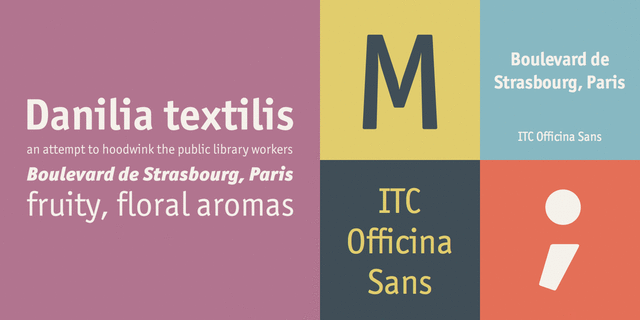
Гарнитура разработана в фирме International Typeface Corporation в 1990 году (дизайнер Эрик Шпикерман). Гротесковая версия шрифта ITC Officina Serif. Основанный на близких пропорциях, насыщенности и форме знаков, этот шрифт сохраняет ту же силу, что и его антиквенный компаньон. Легко читаемый, экономичный и крепкий, он предназначен для офисной корреспонденции, но имеет широкое применение в рекламе и акциденции. Дополнительные начертания и капительные знаки разработаны в 1998 году (дизайнер Оле Шёфер). Кириллическая версия 4-х начертаний разработана в фирме ПараТайп (ПараГраф) в 1994 (дизайнер Тагир Сафаев). Дополнительные начертания и капительные знаки кириллицы разработаны для фирмы ParaType в 2002 году (дизайнер Изабелла Чаева). Греческий набор знаков разработан Паносом Харатзопулосом из Cannibal Fonts в 2000 году.
спокойный, ровный, универсальный, понятный, простой, нейтральный, средний, обычный, деловой, уравновешенный, космополитичный, ненавязчивый, стандартный, умеренный, техничный, прямой, современный, глобализированный, глобалистичный, монотонный, точный, объективный, логичный, неброский, прагматичный, практичный, оптимальный, твердый, невыразительный, лаконичный, доступный, доверительный, комфортный, городской, строгий, серьезный, безразличный, равнодушный, офисный, официальный, культурный, гуманитарный, образованный, умный, удобный, качественный, вежливый, плотный, убедительный